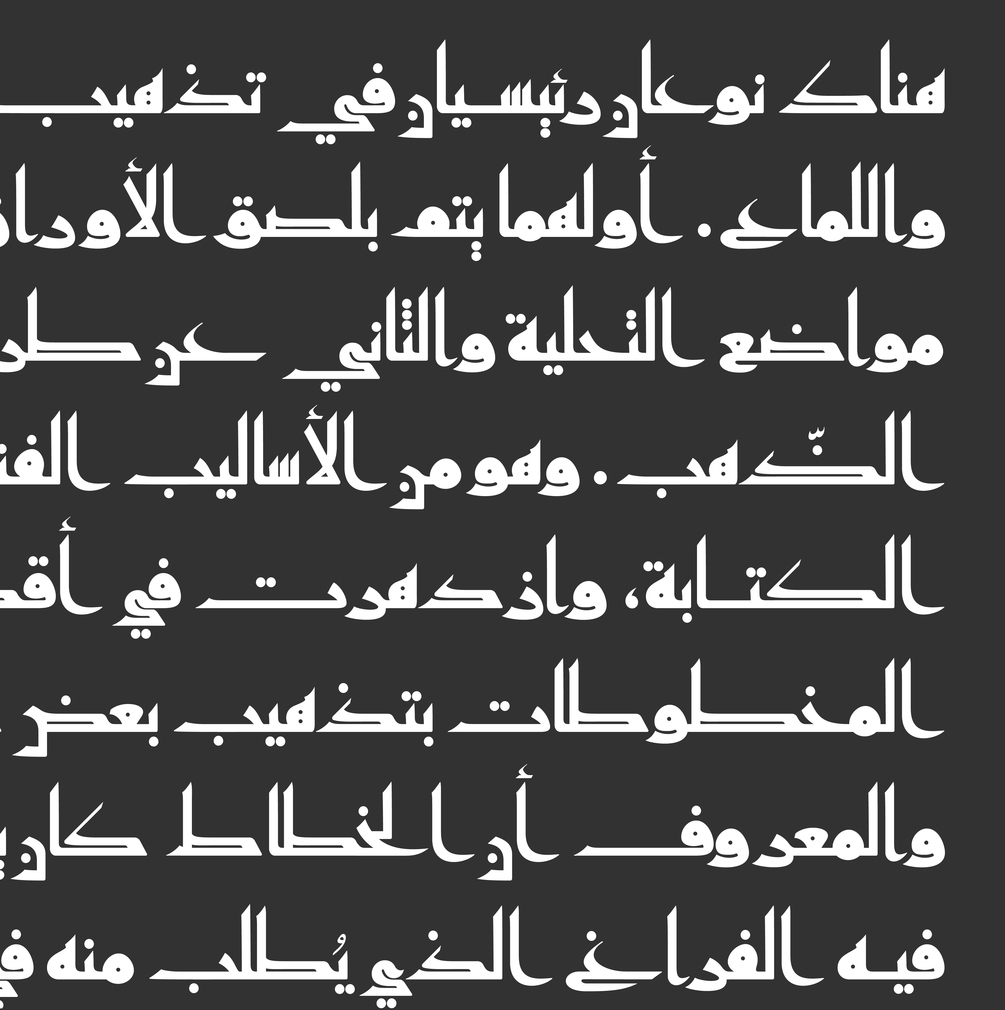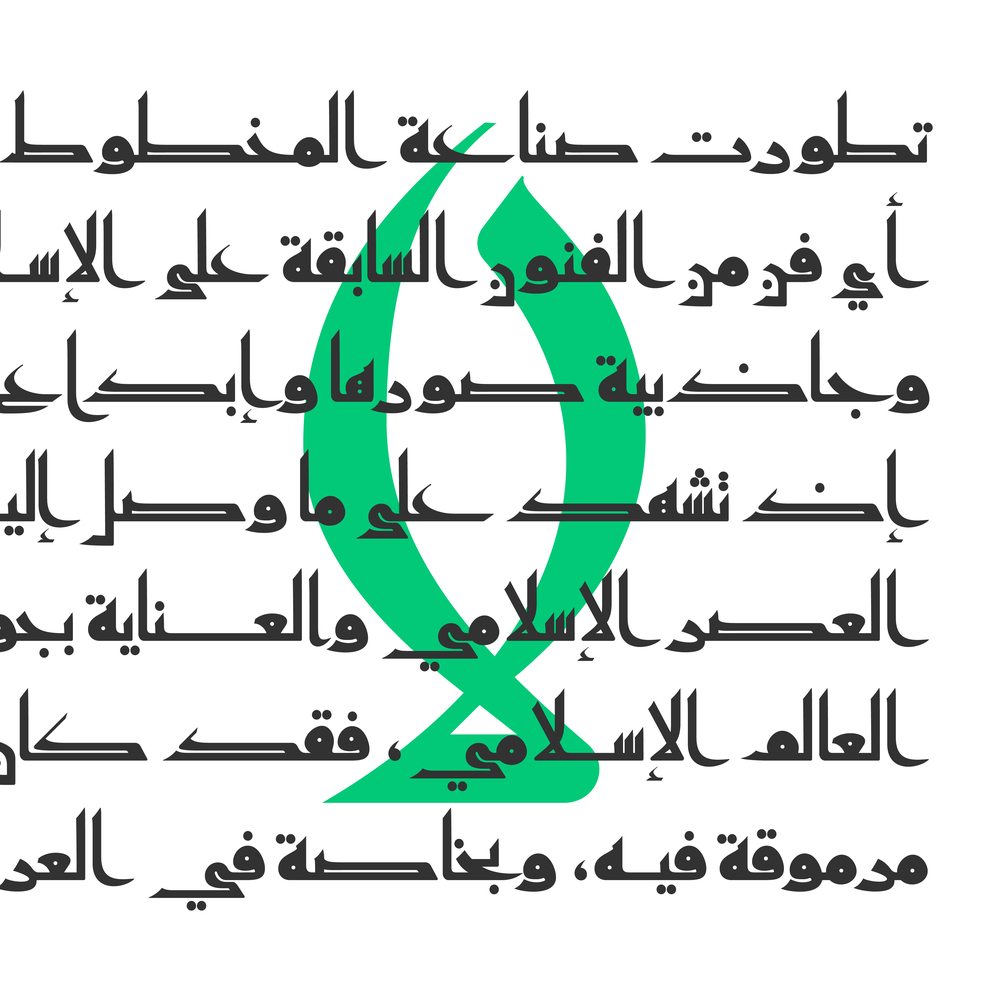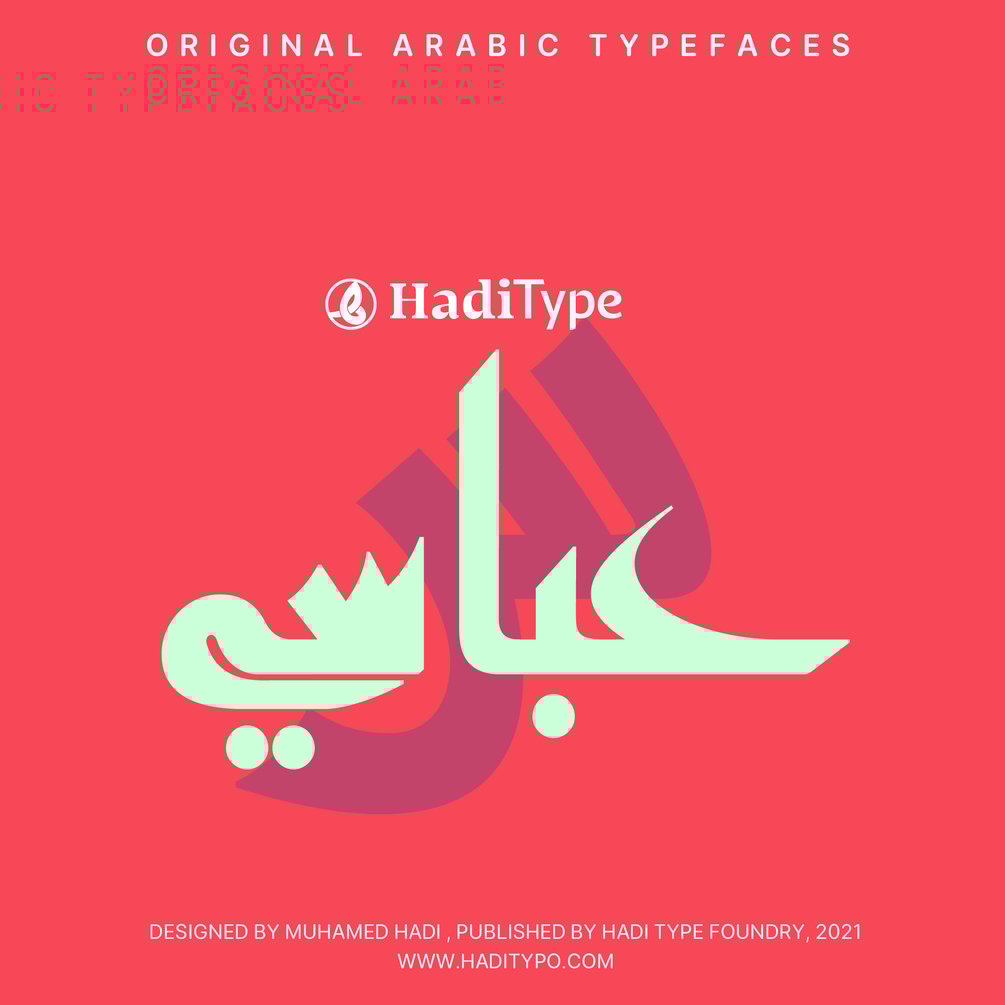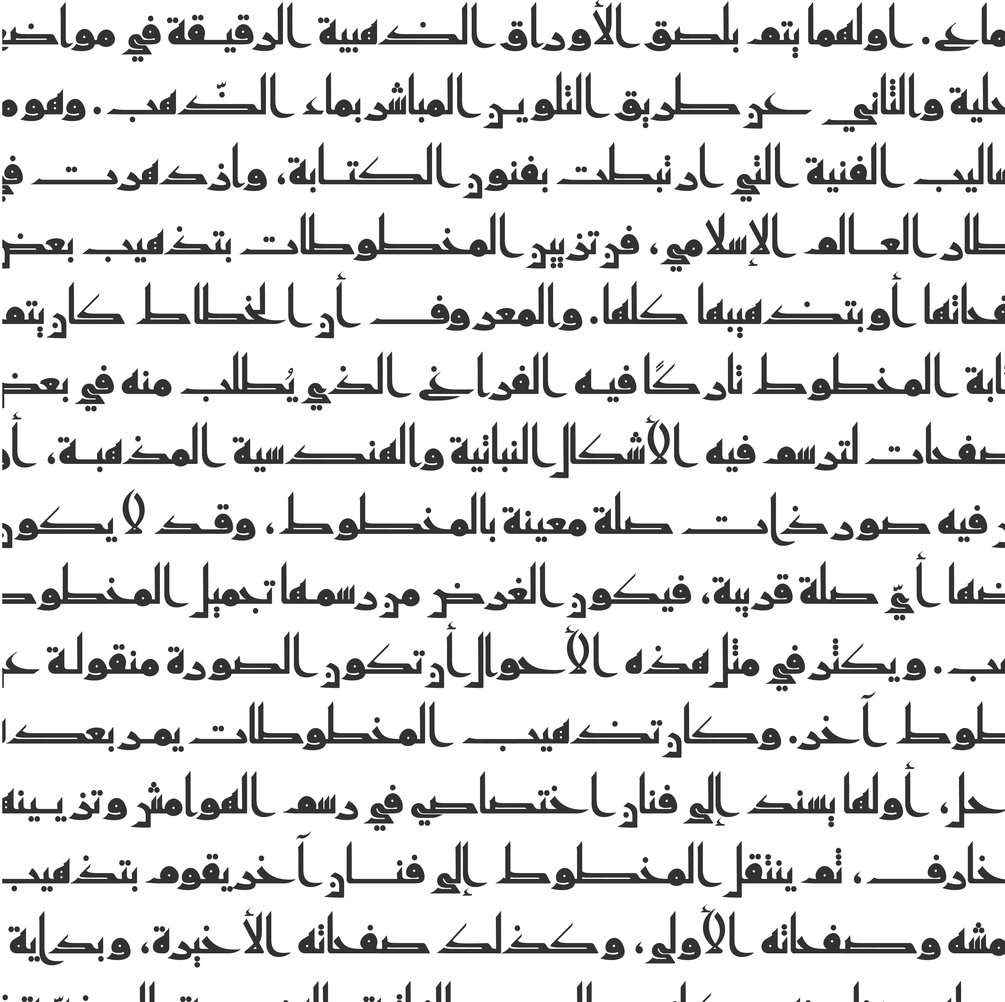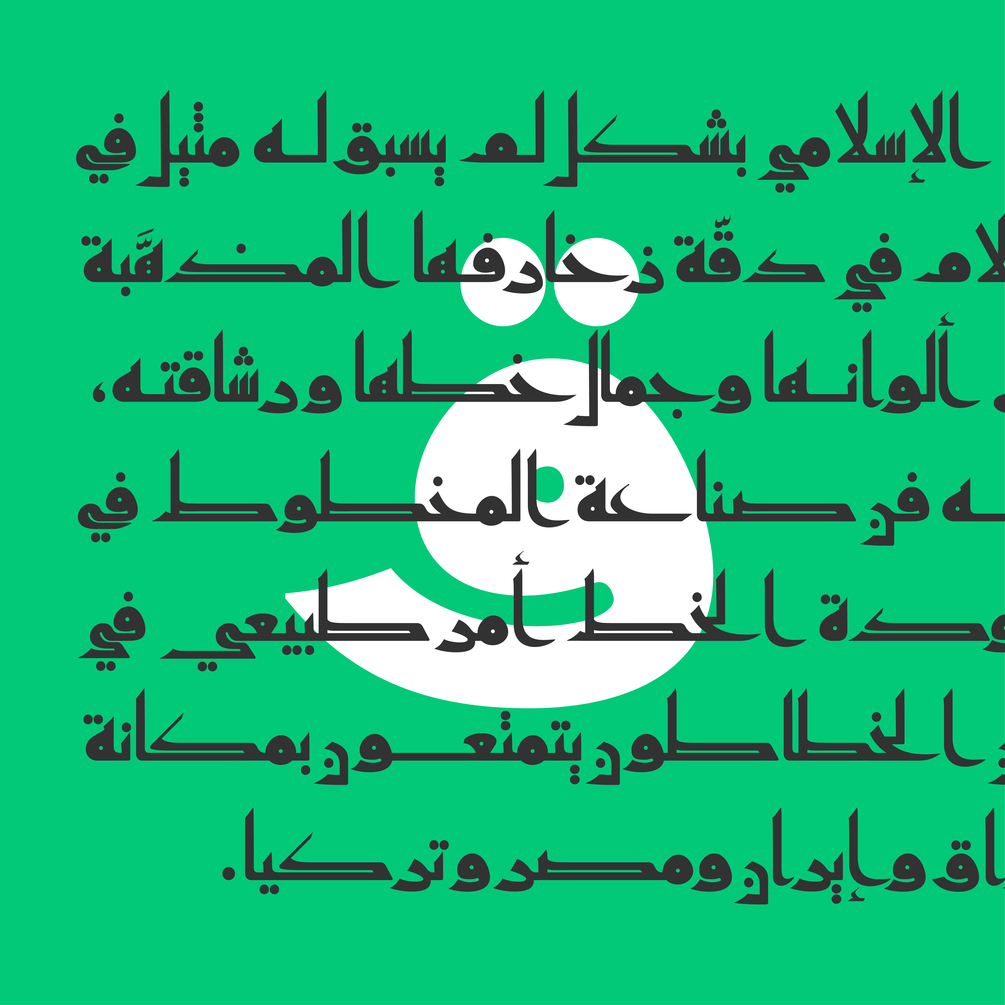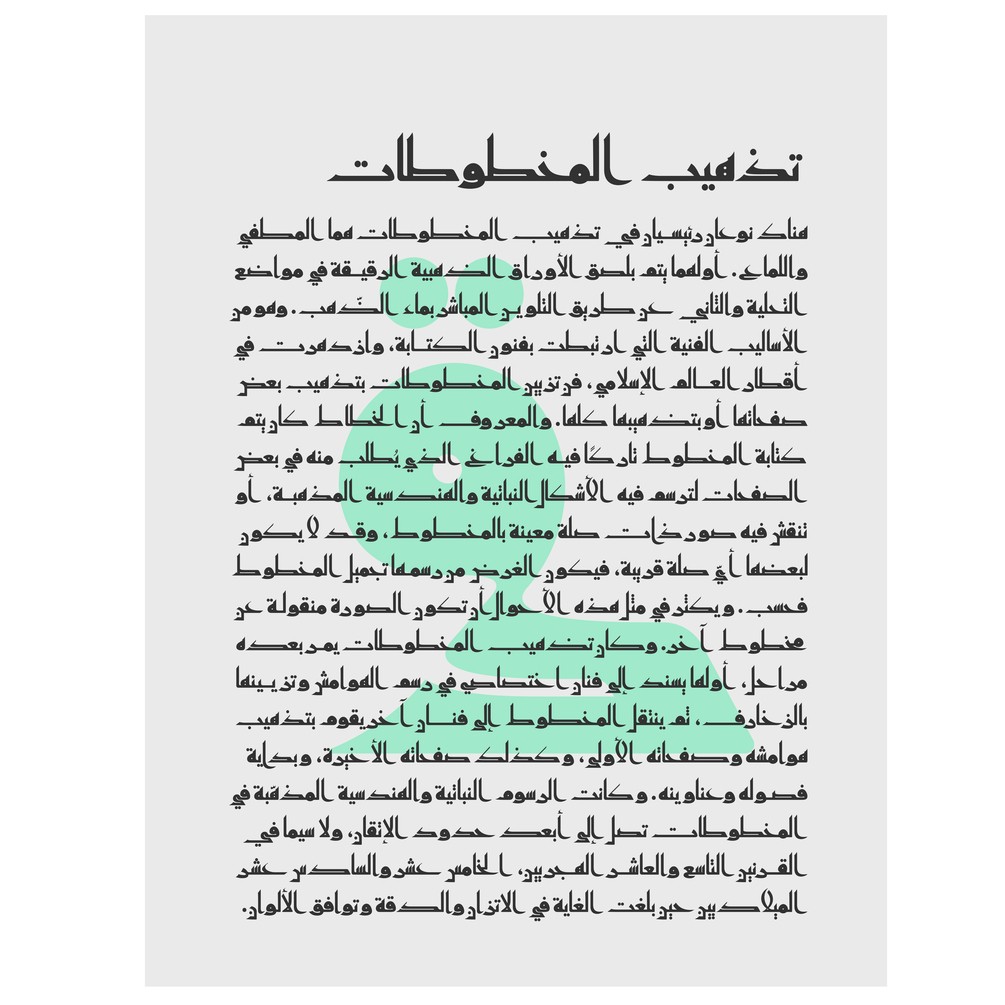
HT Abassi
«عباسي» هو خط عناوين رئيسي عربي حديث تم تطويره في الأصل بشكل بسيط، تصميمه يذكرنا بأعمال الخط العربي من القرنين التاسع والعاشر الميلاديين والتي كانت عادةً ما تكتب بالحبر والذهب على الرق، تعطي المعالجة القوية التي ادخلتها على بعض محارف طراز الخط الأصلي التقليدي إحساسًا عصريًا وتمنح المزيد من سهولة القراءة والوضوح.
تضفي نسب الخط المتباينة بين السماكات الرأسية الطويلة والسماكات الأفقية إلى حد ما مظهرًا تذكاريًا على خط «عباسي»، مما يجعل من استخدامه للعناوين إختيار موفق.
خلال السنوات الماضية تم تطوير خط «عباسي» إلى خط أوبن تايب متقدم، مع إضافة العديد من الأشكال البديلة مثل (الحاء، الجيم، الخاء، الراء، الزين، العين، الغين، السين، الشين واللام ألف) لتمنح الخط سهولة القراءة والوضوح التام.
«عباسي» من إنتاج شركة حروف هادي من 2019 إلى 2021، رسم محمد هادي.
«Abassi» is a modern Arabic headline face Originally developed as a simplified face, its design recalls the Arabic Calligraphy works from the 9th–10th century which usually written with Ink and gold on parchment, The strong treatment of some letters gives the traditional style a modern feel to the design & for more readability and legibility.
The contrasting proportions of the tall vertical strokes and horizontal strokes lend a monumental look to «Abassi», allowing its effective use in titling.
During the years «Abassi» was developed into an Advanced OpenType typeface, with the addition of many alternates forms like (hah, jeem, khah, reh, zain, ain, ghain, seen, sheen & lam_alef) to improve character readability, spacing, and balance.
«Abassi» produced by HadiType Foundry from 2019 to 2021, drawn by mohammed_abdelhadi.